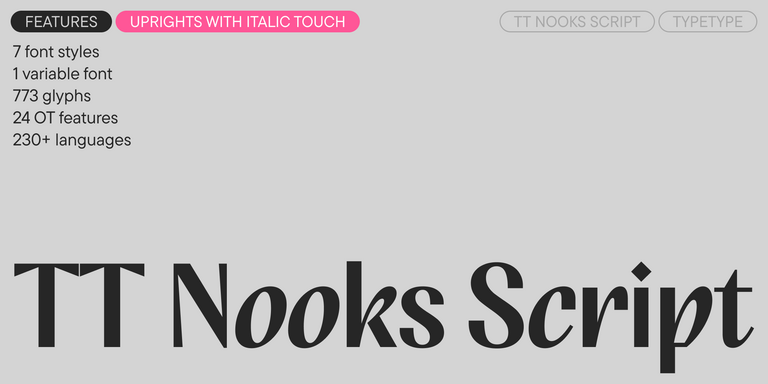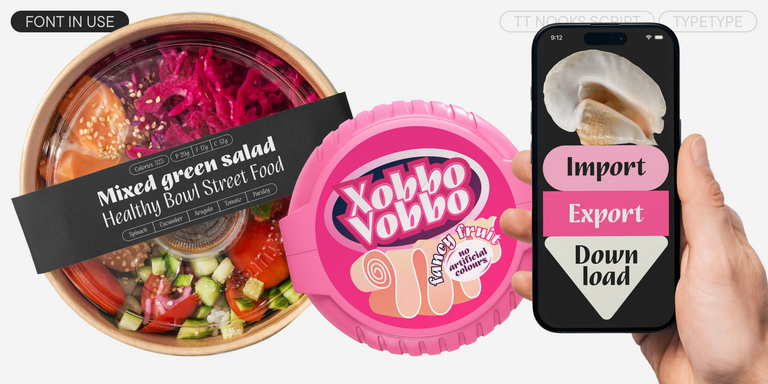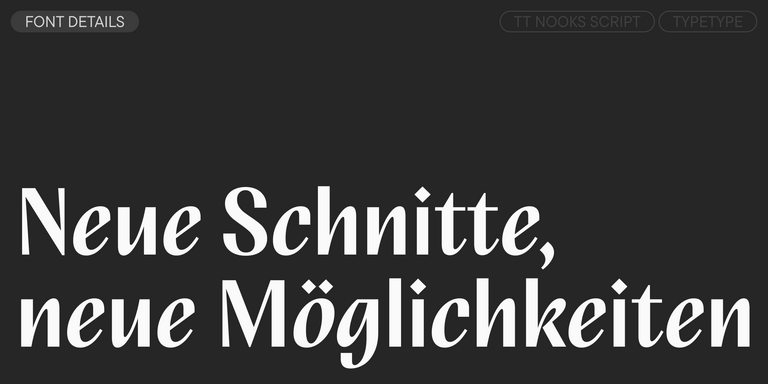
TT Polihaus ist eine experimentelle Grotesk, die auf den ersten Blick konventionell wirkt, sich dann jedoch zunehmend in einzelne Elemente auflöst und schließlich eine stencilartige Struktur annimmt.
Roblox-Schriften
TT Nooks Script besitzt eine eigenständige Zeichnung, für die es kaum direkte Vergleichspunkte gibt.
TT Dott ist eine experimentelle Pixel-Grotesk, die den Kreis zur Grundlage des Pixels macht. Sie ist eine plastische, ungewöhnliche Akzidenzschrift und weckt zugleich Assoziationen an Stickerei und Techno-Partys.
TT Supermolot Neue ist eine neu gestaltete, erweiterte und deutlich verbesserte Reinkarnation der beliebten Schriftfamilie.
TT Rationalist ist eine funktionale und neutrale Slab-Serif-Schrift.
TT Modernoir ist eine Display-Sans-Serif mit dynamischen Proportionen. Fließende Linien und feine Jugendstilformen verschmelzen in dieser Schrift harmonisch mit dem rhythmischen Fluss und der improvisatorischen Freiheit des Jazz.
TT Fors ist eine moderne geometrische Sans Serif mit Zeichen und Formen, die sich in ihrer Breite kontrastreich unterscheiden.
TT Gertika ist eine geometrische Sans Serif mit dynamischem Charakter und tänzerischem Rhythmus. Die Idee dieser Schrift stammt von einem amerikanischen Plakat aus den späten 1930er-Jahren.
TT Biersal ist eine Display-Sans-Serif mit freigeistigem, verspieltem und abenteuerlustigem Charakter. Das Konzept dieser Schrift wurde von einem deutschen Plakat aus den frühen 1930er-Jahren inspiriert.
TT Tricks ist eine moderne Textserif, deren Design den Stil von Transitional-Serifen widerspiegelt. Die Schrift besitzt einen ruhigen, eleganten und maßvoll strengen Charakter.
TT Cometus ist eine ausdrucksstarke Schrift, die vom ersten Moment an fesselt.
TT Octosquares ist eine frische, überarbeitete, erweiterte und deutlich verbesserte Version unserer ersten kommerziellen Schrift TT Squares und ihrer schmalen Variante.
TT Ricks ist eine extravagante Serifenschrift im Elzevir-Stil, für die Wörter wie „süß“ oder „ruhig“ definitiv nicht passen.
TT Carvist ist eigenwillig, verspielt und mutig — eine Schrift, die Aufmerksamkeit hervorragend auf sich zieht.
Eine technologische Schriftfamilie für Game Design.
TT Bluescreens ist eine verbesserte geometrische Sans Serif mit schmalen Proportionen.
Ausgangspunkt des Projekts TT Trailers war die Idee, eine neue Generation schmaler Schriften für den Einsatz in Filmabspännen und Plakaten zu entwickeln.
TT Autonomous ist eine moderne Techno-Grotesk mit breiten, kantigen Proportionen.
TT Berlinerins ist eine Grotesk, inspiriert von Holzlettern auf Plakaten aus dem ersten Drittel des 20. Jahrhunderts, und bringt die historische Komponente Berlins zum Ausdruck.
TT Octas ist eine schmal proportionierte Schriftfamilie, die auf dem Prinzip achteckiger Formen basiert: Alle Kreise in dieser Schrift sind tatsächlich Oktagone. Dank kleiner Serifen besitzt TT Octas einen ausgeprägten Vintage-Charakter.
TT Bricks ist die Antwort für Liebhaber sowjetischer Kultur. Wir haben versucht, hundert Jahre zurückzugehen und die Ära des Konstruktivismus neu zu interpretieren.